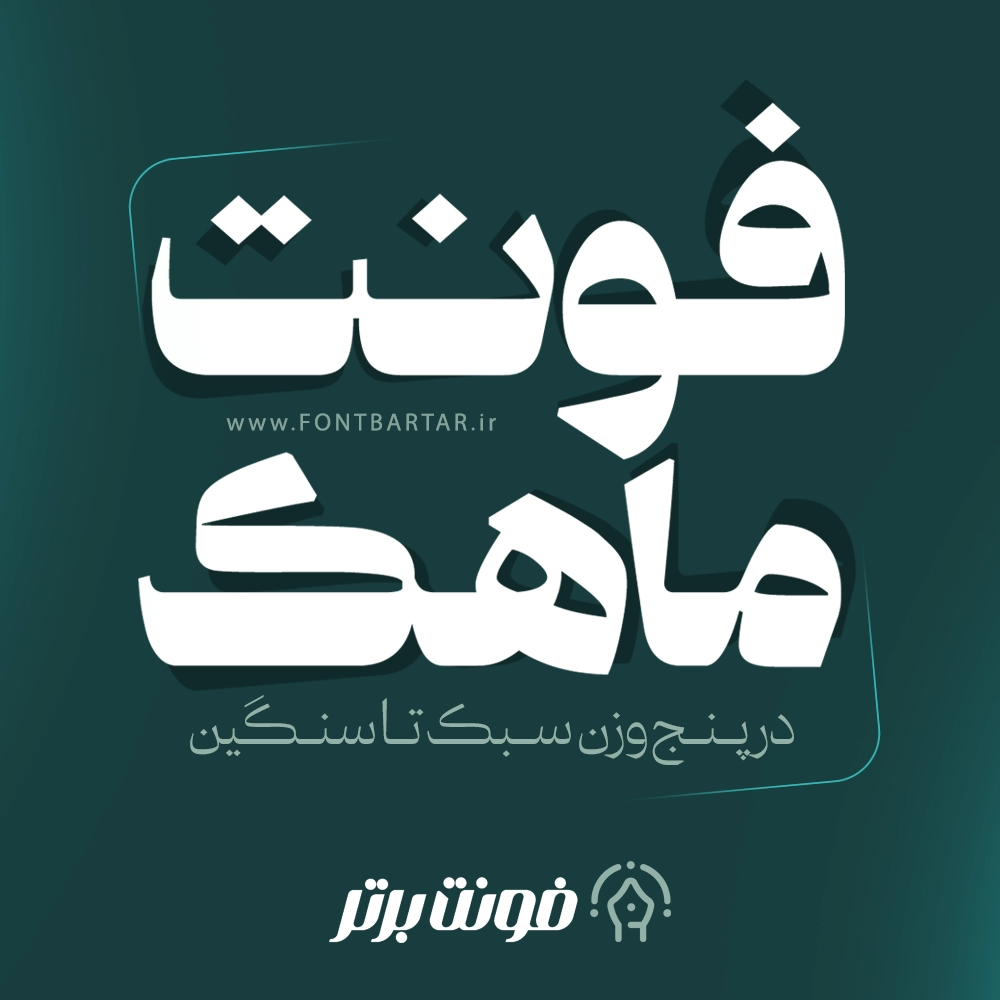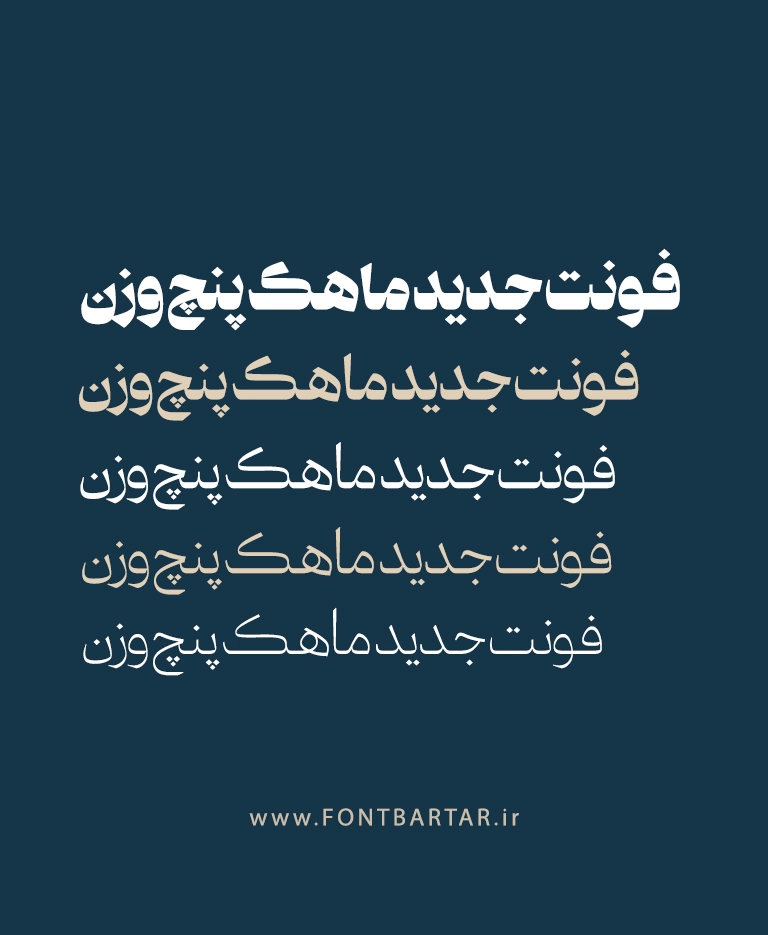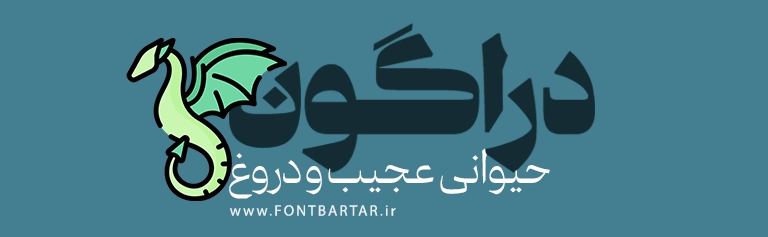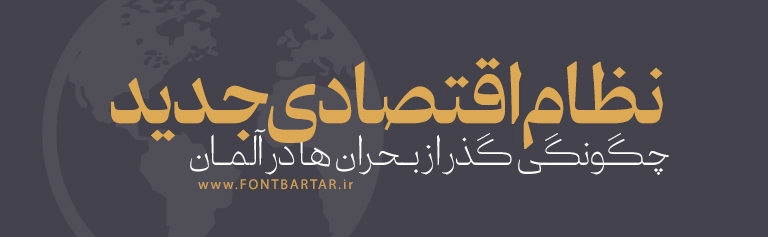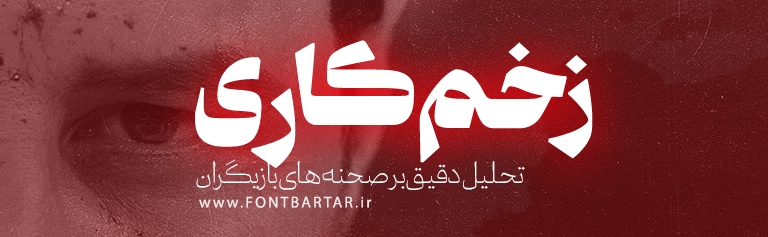
فونت جدید ماهک یکی از جدیدترین فونتهای فارسی با طراحی مدرن و سبک نازکین است که در ۵ وزن متنوع ارائه شده و انتخابی عالی برای طراحان گرافیک، تولیدکنندگان محتوا و برندها محسوب میشود. این فونت جدید فارسی با حفظ خوانایی بالا و فرم حرفهای، برای استفاده در پروژههای دیجیتال و چاپی کاملاً مناسب است.
ویژگیهای فونت فارسی ماهک
فونت ماهک با در نظر گرفتن استانداردهای تایپوگرافی فارسی طراحی شده و نیاز طراحان حرفهای را بهخوبی پاسخ میدهد:
- ✅ دارای ۵ وزن استاندارد (مناسب تیتر و متن)
- ✅ خوانایی بالا در سایزهای مختلف
- ✅ مناسب طراحی پوستر، بنر، لوگو و شبکههای اجتماعی
- ✅ هماهنگ با طراحی مینیمال و مدرن
کاربردهای فونت فارسی در طراحی
اگر به دنبال یک فونت فارسی خاص و چندمنظوره هستید، فونت ماهک انتخابی ایدهآل برای شماست:
- طراحی پوستر تبلیغاتی
- ساخت کاور اینستاگرام و استوری
- طراحی لوگو فارسی
- استفاده در وبسایت و رابط کاربری (UI)
- پروژههای چاپی و دیجیتال
چرا دانلود فونت ایرانی جدید پیشنهاد میشود؟
فونت ماهک نه تنها از نظر ظاهری جذاب است، بلکه از نظر فنی نیز کاملاً استاندارد بوده و با داشتن وزنهای متنوع، انعطاف بالایی در طراحی ایجاد میکند. این ویژگی باعث میشود بدون نیاز به چند فونت مختلف، تنها با فونت جدید ترند تمام نیازهای تایپوگرافی خود را پوشش دهید.
FAQ (سؤالات متداول)
فونت ماهک چند وزن دارد؟
فونت جدید تایپوگرافی فونت ماهک شامل ۵ وزن متنوع است که برای تیتر، متن و طراحی حرفهای کاملاً کاربردی هستند.
آیا فونت ماهک برای اینستاگرام مناسب است؟
بله، این فونت به دلیل خوانایی بالا و طراحی مدرن، برای کاور پست، استوری و ریلز اینستاگرام بسیار مناسب است.